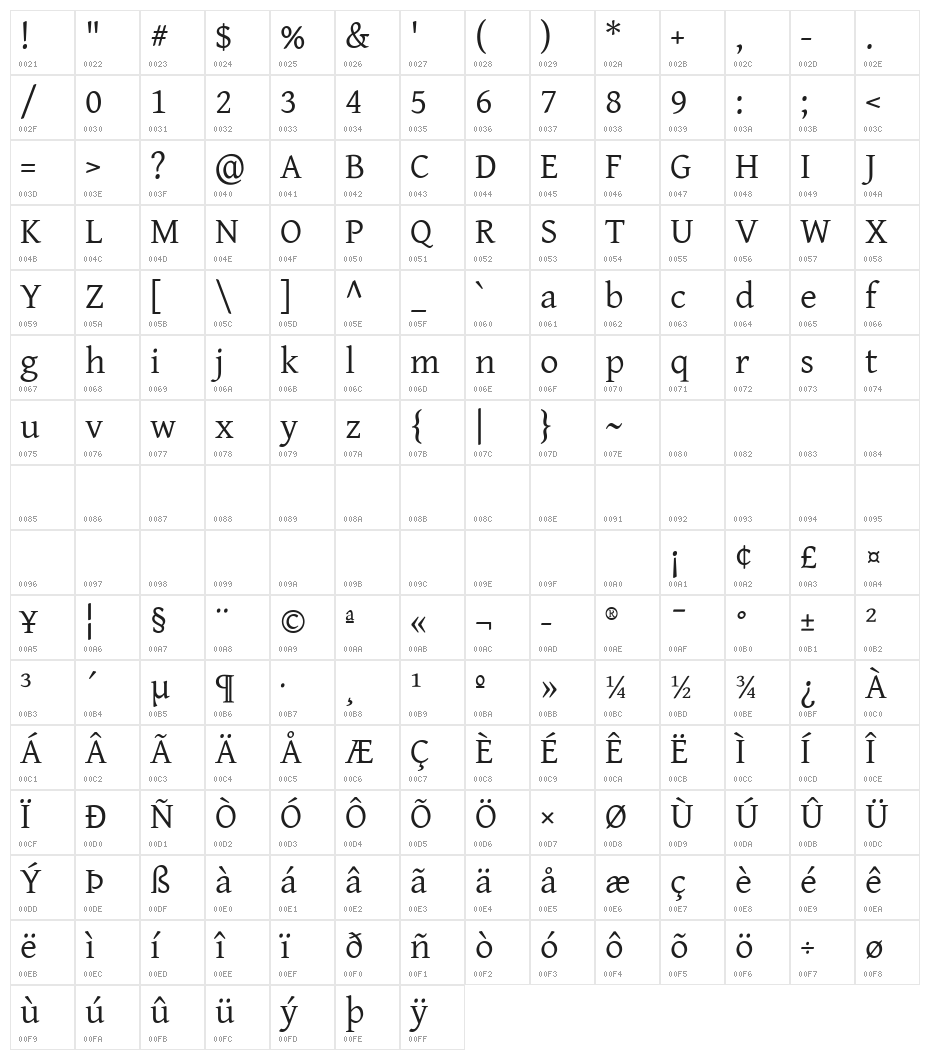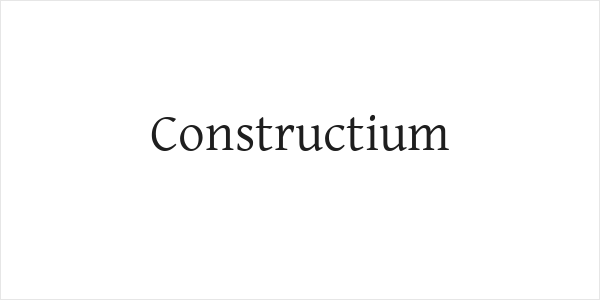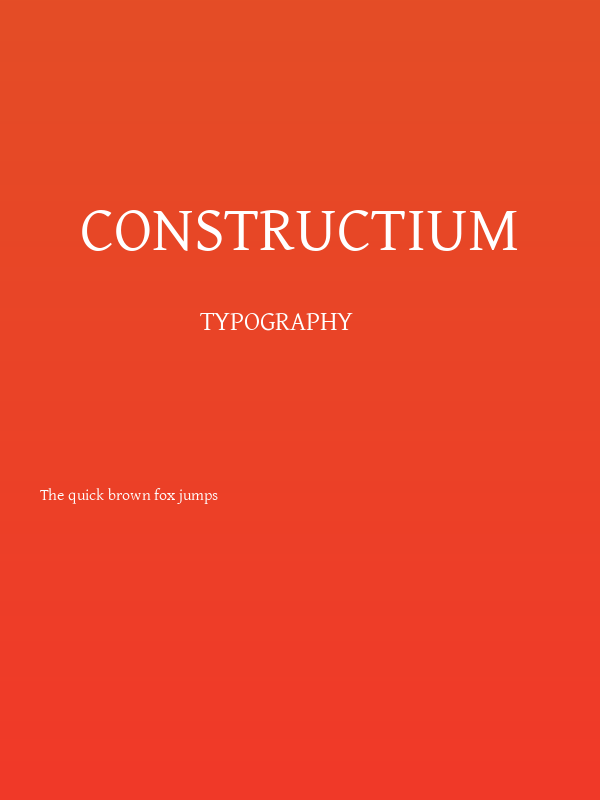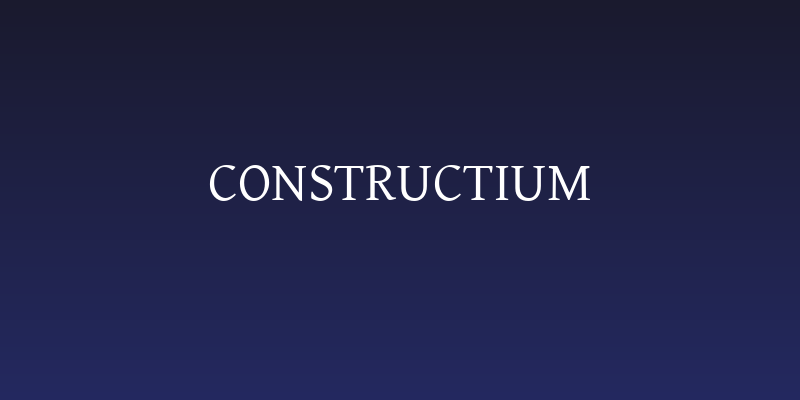
Constructium Font
| Proiecte propuse | Ideal for editorial design, book covers, formal invitations, and branding projects that require a touch of elegance. |